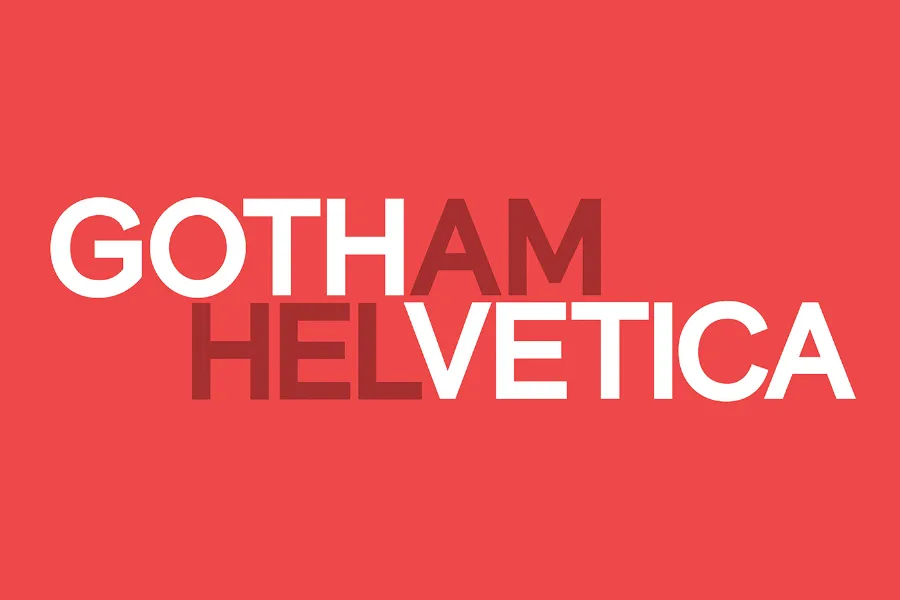
A Gothvetica Font foi criada por Mark Studio, explorando a interseção entre duas icônicas fuentes do tipo: Gotham e Helvetica. Este interessante projeto começa com uma simples pergunta: “Como assemelham-se Gotham e Helvetica como tipos de letra? O que seria de Gotham e Helvetica se fossemem mesclados?” A Gothvetica é um mergulho na essência das duas fontes: a elegância moderna da Helvetica e o encanto gótico das linhas seráficas de Gotham. Ela combina elementos contemporâneos com uma dose suave de nostalgia, oferecendo designers um recurso versátil para projetos que vão desde logotipos dinâmicos até textos legíveis em ambientes digitais. Com uma aparência acurada e sofisticada, a Gothvetica é ideal tanto para criar experiências digitais modernas quanto para trazer algo de inovador às atmosferas mais tradicionais. Esta fonte é perfeita para quem procura um equilíbrio harmonioso entre estética futurista e uma sensação nostálgica, tornando-se uma opção elegante para qualquer projeto que valorize a interseção de diferentes influências estéticas. Estamos animados com essa novidade da Mark Studio, uma fonte de qualidade que oferece um design único e versátil capaz de moldar os mais variados tipos de projetos gráficos.